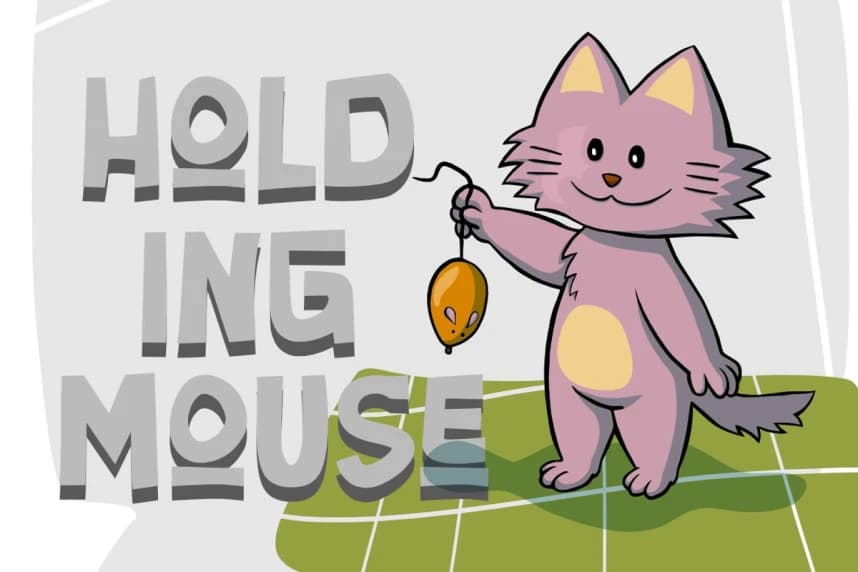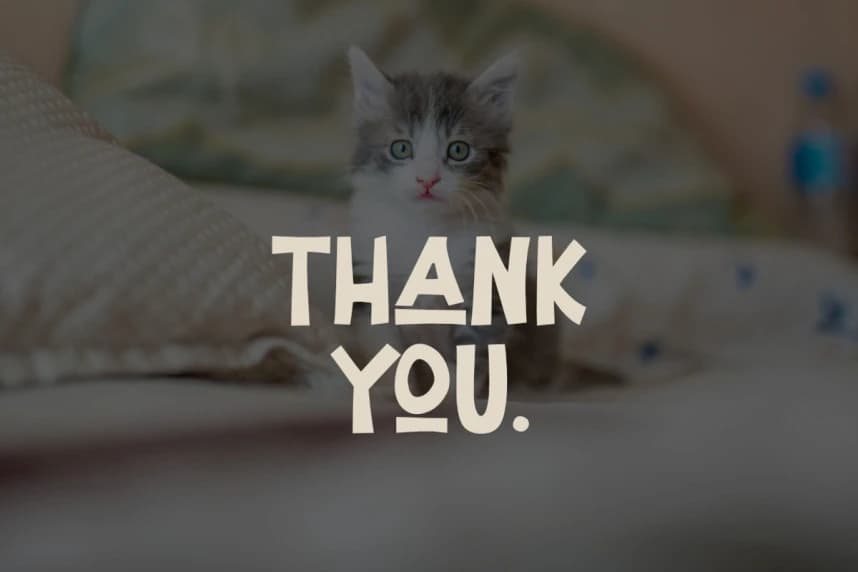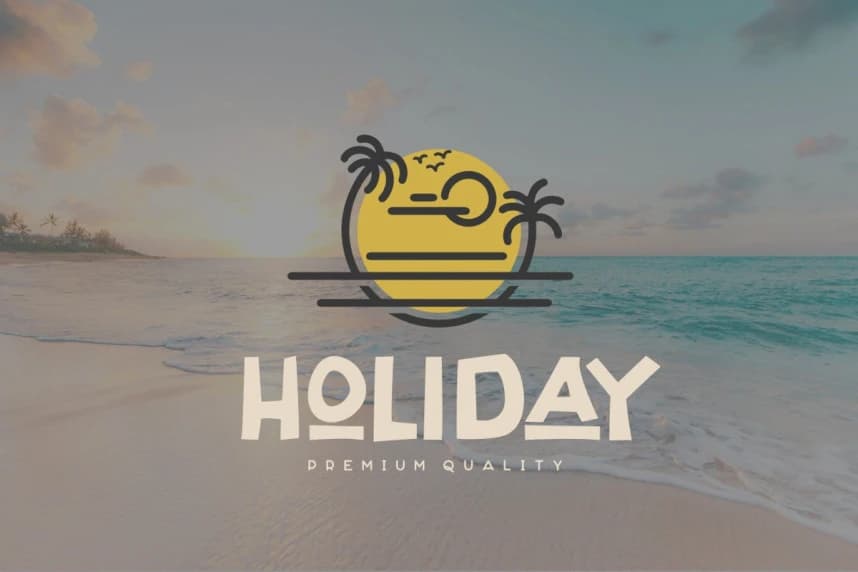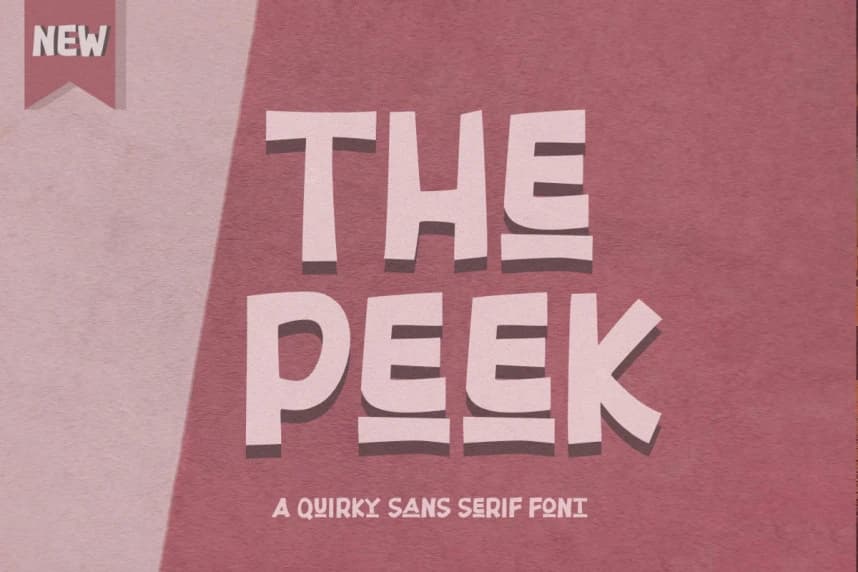
The Peek Font
The Peek Font - Quirky Sans Serif Font, Bu font, yüksek kaliteli bir üretim standardına sahiptir ve şu amaçlarla kullanabilirsiniz: broşürler, alıntılar, posterler, afişler, bannerlar, ambalajlar, ticari ürünler, logotipler ve çok daha fazlası.
The Peek Font - Quirky Sans Serif Font, Bu yazı tipi yüksek kaliteli bir seviyede üretilmiştir ve afişler, alıntılar, posterler, pankartlar, ambalajlar, ticari ürünler, logotipler ve çok daha fazlası için kullanılabilir.